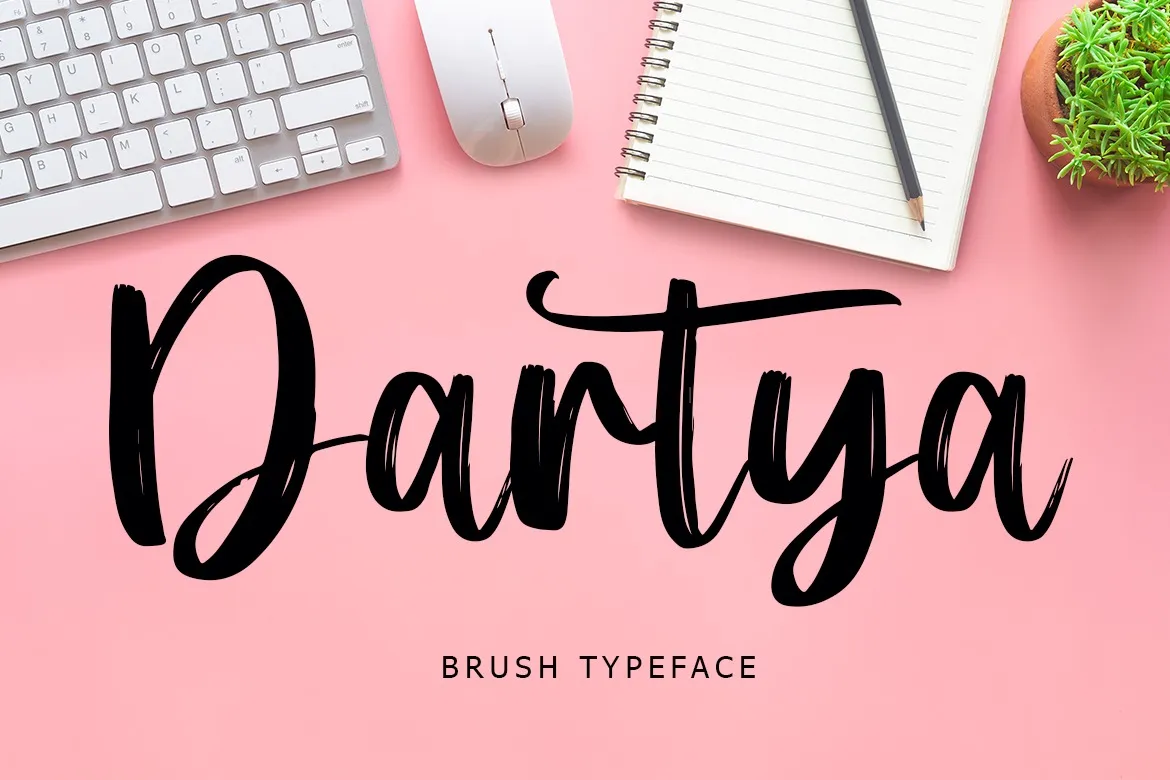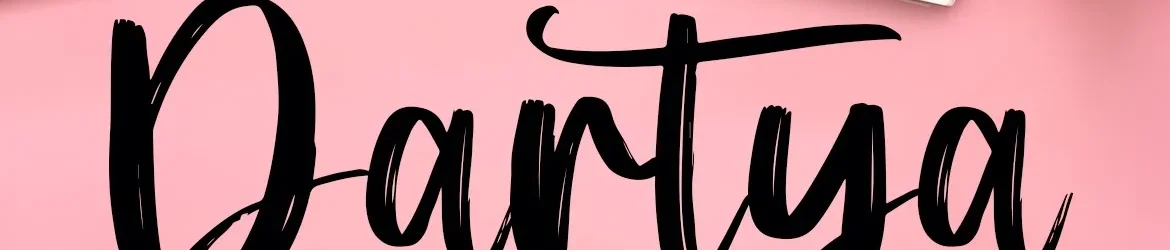
A Dartya Font é uma elegante e delicada fonte de script produzida pela designer lyanatha. Esta herança única e natural do estilo da esponja oferece flexibilidade para um vasto leque de projetos gráficos. Com seu traço suave, a Dartya se destaca em estilos variados como cartazes publicitários, logotipos e design editorial. Ela é perfeita tanto para criações modernas quanto para soluções mais vintage, garantindo que sua visão seja única, desde que seu imaginário não tenha limites. Em um mundo de texturas digitais, a Dartya Font proporciona uma experiência sensorial natural e autêntica.